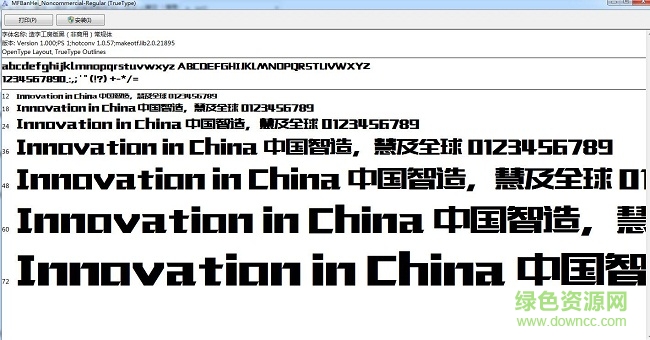
mfbanhei是什么字體?mfbanhei_nonconmmercial regular 字體就是造字工房版黑(非商用)常規(guī)體,美觀實用,綠色資源網(wǎng)還有更多好看的字體和廣告字體可供大家免費下載使用!
1.造字工房版黑體的筆畫字形設(shè)計尖銳剛正,字體特點厚重不失精干;
2.扁平的字形特點使其沉穩(wěn)低調(diào),字形本身也有著良好的識別性和設(shè)計特征;
3.適用于標(biāo)題用字,有著較廣泛的選擇和應(yīng)用性。